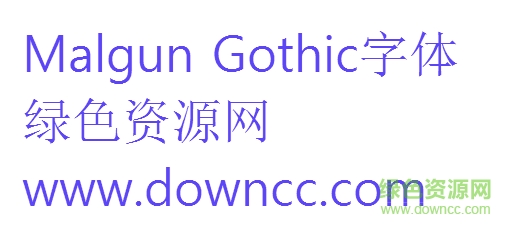
Malgun Gothic
malgun gothic是vista系統(tǒng)的默認(rèn)韓語(yǔ)字體,字形干練大氣,是一款氣質(zhì)優(yōu)美的系統(tǒng)字體,字庫(kù)較全,方便用戶更好的進(jìn)行韓文書寫,來(lái)綠色資源網(wǎng)免費(fèi)下載吧!
malgun gothic字體簡(jiǎn)介
맑은고딕(Malgun Gothic):這款字體名稱大家應(yīng)該都有點(diǎn)印象吧。微軟為了應(yīng)用ClearType和雅黑同期推出的韓文字體,同時(shí)也是韓文vista的系統(tǒng)默認(rèn)字體。
malgun gothic
怎么說呢。。個(gè)人感覺并不是特別好看的一款字體,在某些網(wǎng)頁(yè)下帶下劃線的文字還會(huì)出現(xiàn)下沉的現(xiàn)象。。微軟字體中第一款字形為長(zhǎng)方形的韓文字體(之前全是正正方方的),個(gè)人認(rèn)為長(zhǎng)方形的韓語(yǔ)字更漂亮。遺憾的是這款字體只包含完整的韓語(yǔ)字符,漢字字符一個(gè)也沒有。。